Почему Apple решила заменить системный шрифт в iOS 9 и OS X 10.11
Как известно, Apple приняла решение заменить шрифт в смартфонах, планшетах и компьютерах. Вместо Helvetica Neue компания введет новый шрифт San Francisco в своих операционных системах. В данный момент он используется на Apple Watch и на клавиатурах 12-дюймовых MacBook с дисплеем Retina.
Причины такого перехода объяснил эксперт в области дизайна Вентинг Жанг. По его словам, шрифт San Francisco «чёткий и хорошо различимый», он лучше читается, чем нынешний Helvetica Neue. В рамках проекта Type Detail Жанг продемонстрировал преимущества такого написания.
Одним из аспектов San Francisco эксперт назвал «увеличенное на вертикали начертание». Строчные буквы составляют около 75% от прописных – больше, чем у большинства других шрифтов. «Глаз» в буквах, таких как «е» или «а» – расстояние между хвостом и остальной частью – больше, чем в обычных шрифтах. Эти особенности начертания повышают «читабельность» текста даже при малой величине кегля.
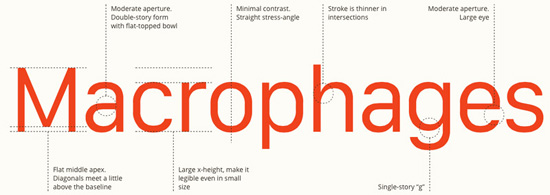
Напомним, что Helvetica Neue появилась в iPhone и iPad с обновления iOS 7 в 2013 году, а в OS X — с обновления OS X Yosemite. Дизайнеры критически отнеслись к этому решению — новый шрифт было непросто читать. «Это просто плохой интерфейсный шрифт, — заявил дизайнер Фрэнк Кимеро. — Низкий контраст, похожие формы и так далее. Буквы сложно отличить друг от друга, особенно в тексте, набранном небольшим кеглем».